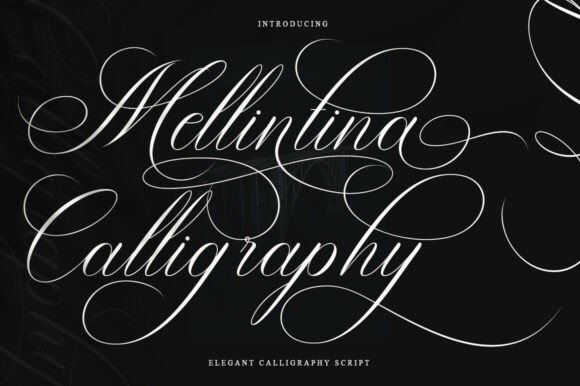
Melintina Calligraphy
Melintina Calligraphy : la police d’écriture élégante qui séduit les créatifs
Vous recherchez une police de caractères qui allie élégance intemporelle et modernité audacieuse ? Melintina Calligraphy répond parfaitement à cette exigence. Conçue avec une précision artisanale, cette police script luxueuse marie la grâce du copperplate traditionnel à des touches résolument contemporaines, offrant ainsi un style à la fois féminin et ultra‑lisible.
Caractéristiques principales
- Variantes de caractères charmantes : chaque lettre possède plusieurs formes alternatives, permettant de créer des compositions dynamiques et personnalisées.
- Courbes raffinées et liaisons uniques : les traits fluides et les raccords ingénieux assurent une esthétique visuelle saisissante.
- Lisibilité exceptionnelle : malgré son allure calligraphique, la police reste claire et facile à lire, même en petite taille.
- Polyvalence professionnelle : adaptée aux invitations, étiquettes, menus de restaurant, packaging, magazines, romans, cartes de vœux et mariages.
Pourquoi choisir Melintina Calligraphy pour vos projets ?
Melintina Calligraphy apporte une touche de sophistication qui transforme instantanément n’importe quel support. Que vous créiez une invitation de mariage, un menu gastronomique, un packaging de cosmétiques ou une mise en page de magazine, cette police confère une aura de luxe et d’authenticité. Son design élégant se prête également aux projets numériques, telles que les bannières publicitaires ou les posts sur les réseaux sociaux, où la distinction visuelle est cruciale.
Utilisations idéales
- Cartes d’invitation et faire‑part de mariage
- Étiquettes de produits haut de gamme (parfums, maquillage, chocolat)
- Menus de restaurants gastronomiques
- Couvertures de livres et chapitres de romans
- Articles de magazines de mode et de beauté
- Papeterie de luxe (papier à lettres, cartes de vœux)
- Publicités imprimées et digitales premium
Conclusion – Un incontournable pour les créatifs exigeants
En résumé, Melintina Calligraphy se distingue comme la police d’écriture qui combine raffinement classique et tendance contemporaine. Son style féminin, ses variations de caractères et sa lisibilité en font le choix idéal pour tout professionnel du design souhaitant offrir à ses clients une expérience visuelle mémorable. Faites l’expérience de la magie calligraphique de Melintina et donnez à vos créations le caractère élégant qu’elles méritent.